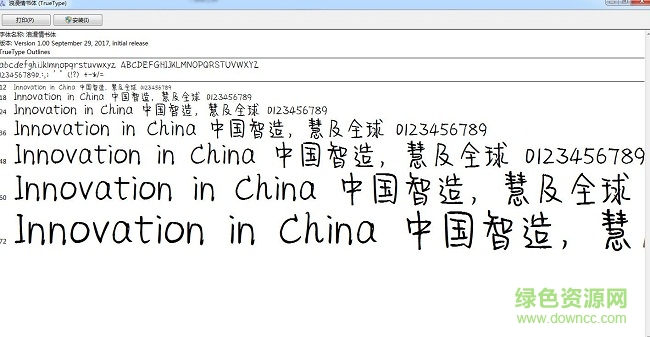
浪漫情書寬距版是在原米開浪漫情書體ttf字體上進(jìn)行美化而來,調(diào)整了字寬,讓文字間更加寬松宜人,給人更加舒適的閱讀體驗(yàn),需要的朋友就來綠色資源網(wǎng)試試吧!
本是一款字形優(yōu)美、風(fēng)格獨(dú)特的字體,增加了字體間距,增強(qiáng)用戶的閱讀體驗(yàn),字體覆蓋率高,適用于手機(jī)閱讀,歡迎大家下載使用!
浪漫情書寬距字體筆畫很精致,字型優(yōu)美,易用耐看,且?guī)в形乃嚉庀ⅲ@是一款硬筆書寫行書字體,瀟灑漂亮,流暢自然,書生氣濃重!